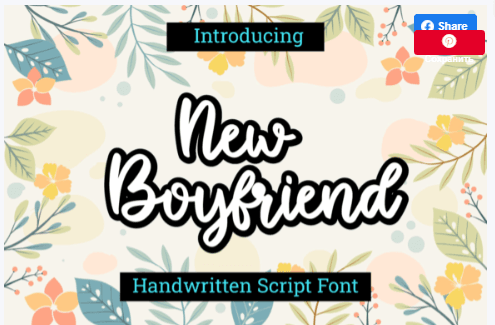
New Boyfriend Font
New Boyfriend - милый, дружелюбный и плавный рукописный шрифт. Этот оригинальный вид подойдет для самых разных творческих идей, от фирменных бланков и заголовков до канцелярских товаров.